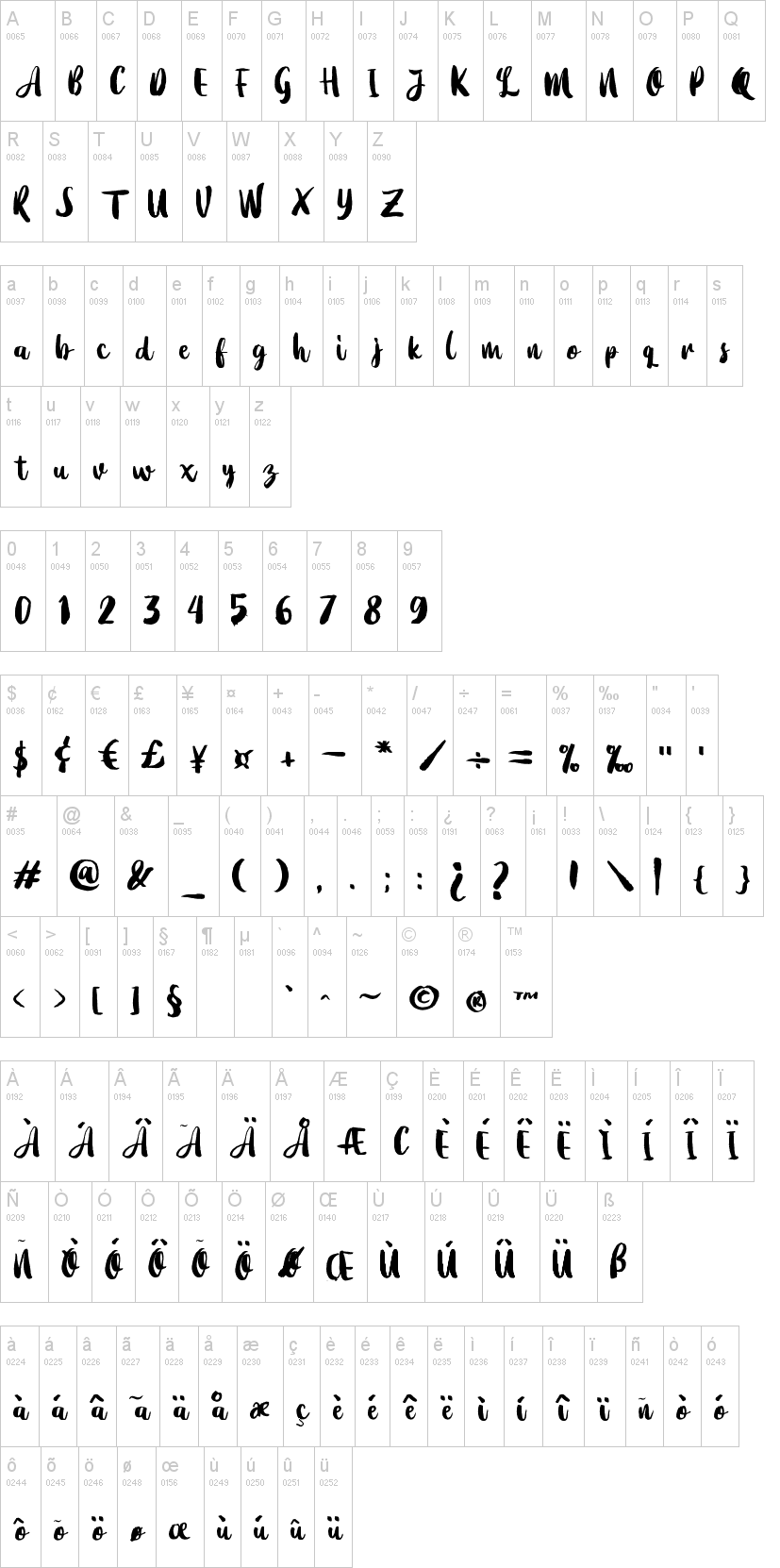
Dearday Script 是一种手写风格的字体,其特点是优美的笔画和流畅的曲线,适用于多种设计场景,特别是与时尚、艺术相关的设计。它的字母形状和大小,以及字母之间的间距都非常平衡,因此非常适合用于标题、标志、广告等具有强烈视觉效果的设计项目中。 Dearday Script 字体由一系列具有笔触变化的字母组成,每个字母都有多个不同的样式,以便在不同的设计场景下使用。该字体提供了多种符号和特殊字符,支持多种语言,包括英语、法语、西班牙语、德语、意大利语等等。 总之,Dearday Script 字体是一种非常适合时尚、艺术、设计等领域的手写字体,它的优美和流畅性使其成为很多设计师首选的字体之一。内容介绍
Dearday Script是一款非常不错的手写艺术字体,具有很好的视觉感,适合于文化类的宣传设计、商业类品牌的广告和产品包装设计以及个性化文字排版等较多场景。